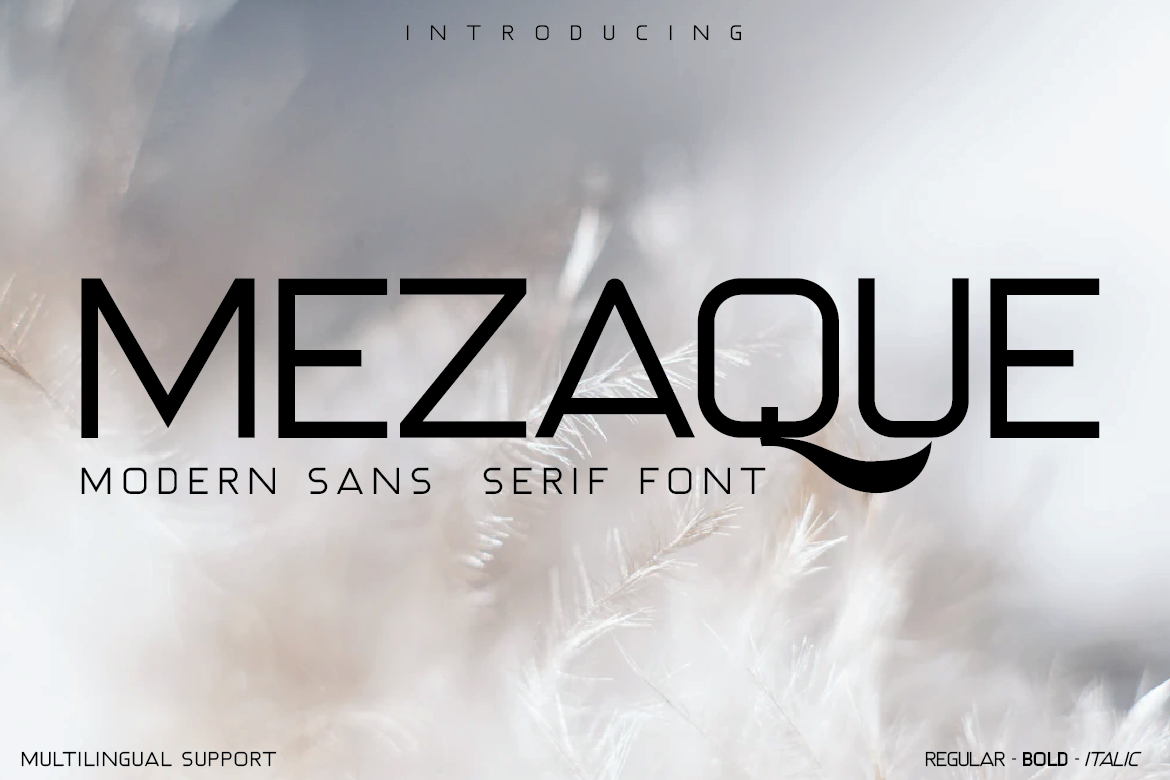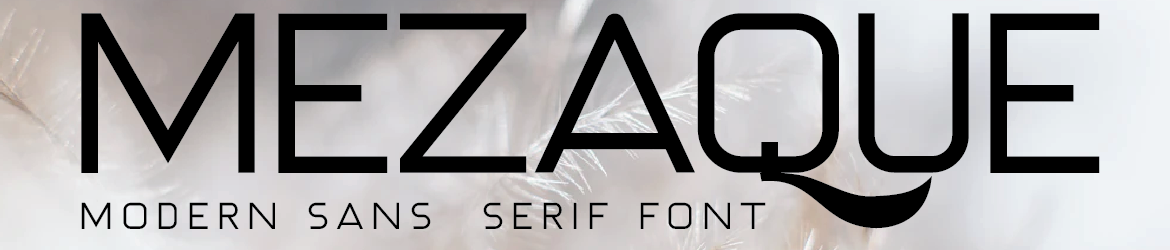
A MEZAQUE Font é uma escolha perfeita para quem deseja adicionar personalidade ao seu design sem perder a simplicidade essencial do tipo livre. Esta fonte sans serif tem um toque distintivo que torna cada palavra de seus designs memorável desde o primeiro olhar. Ela foi criada com cuidado para auxiliar na comunicação, garantindo que a mensagem transmitida em cada projeto seja facilmente reconhecível e lembrada por quem vê. Com seu design limpo e moderno, a MEZAQUE Font é perfeita para aplicar em uma ampla variedade de mídias e propósitos, desde materiais digitais até impressão. Seja você um designer gráfico ou criação de conteúdo digital, a MEZAQUE oferece o que há de melhor em termos de simplicidade e identidade visual. Combinando facilidade de leitura com design atraente, a MEZAQUE é uma escolha inteligente para quem procura se destacar na comunicação visual. Esta fonte foi criada pelo designer brasileiro Anton Septiawan, conhecido por desenvolver materiais gráficos que refletem sua paixão pela arte e tecnologia. Suas criações, como a MEZAQUE Font, oferecem um equilíbrio perfeito entre simplicidade e expressividade, tornando-se um recurso valioso para designers em busca de uma fonte clara e moderna que transmita sua mensagem de forma eficaz.